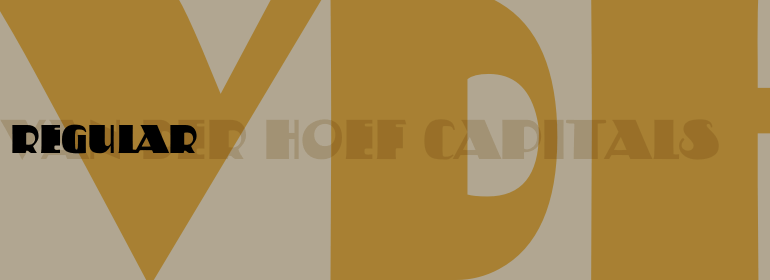
Van Der Hoef Capitals
Van Der Hoef Capitals,这款字体结构工整、笔画清晰,兼顾美观与易读性,适用于标题、正文、海报、包装、LOGO 等多种场景。字形优雅稳定,风格百搭耐看,适配日常排版与创意设计,让文字呈现更舒适、更具质感。Van Der Hoef Capitals一笔一画,皆是细节,以均衡的比例、流畅的线条打造舒适视觉体验,字形端正大气,风格简约现代。无论是商业设计、品牌宣传还是日常排版,都能轻松驾驭,让文字更有格调与力量。Van Der Hoef Capitals字体下载。
字体品牌: Monotype 设计师:Bouwsma,Philip 字体分类:衬线体 字体属性:外文 字符集:Unicode 发布时间: 2018